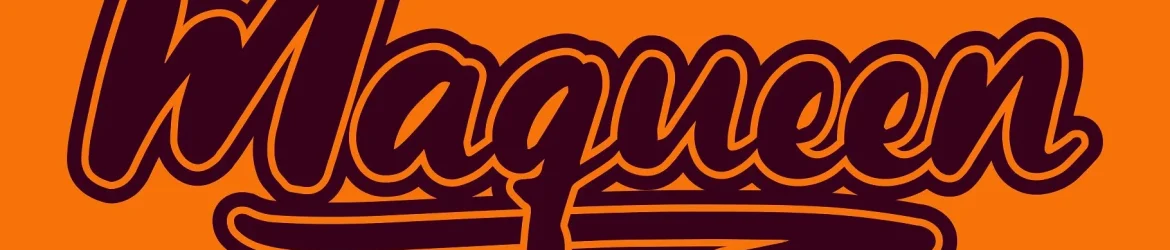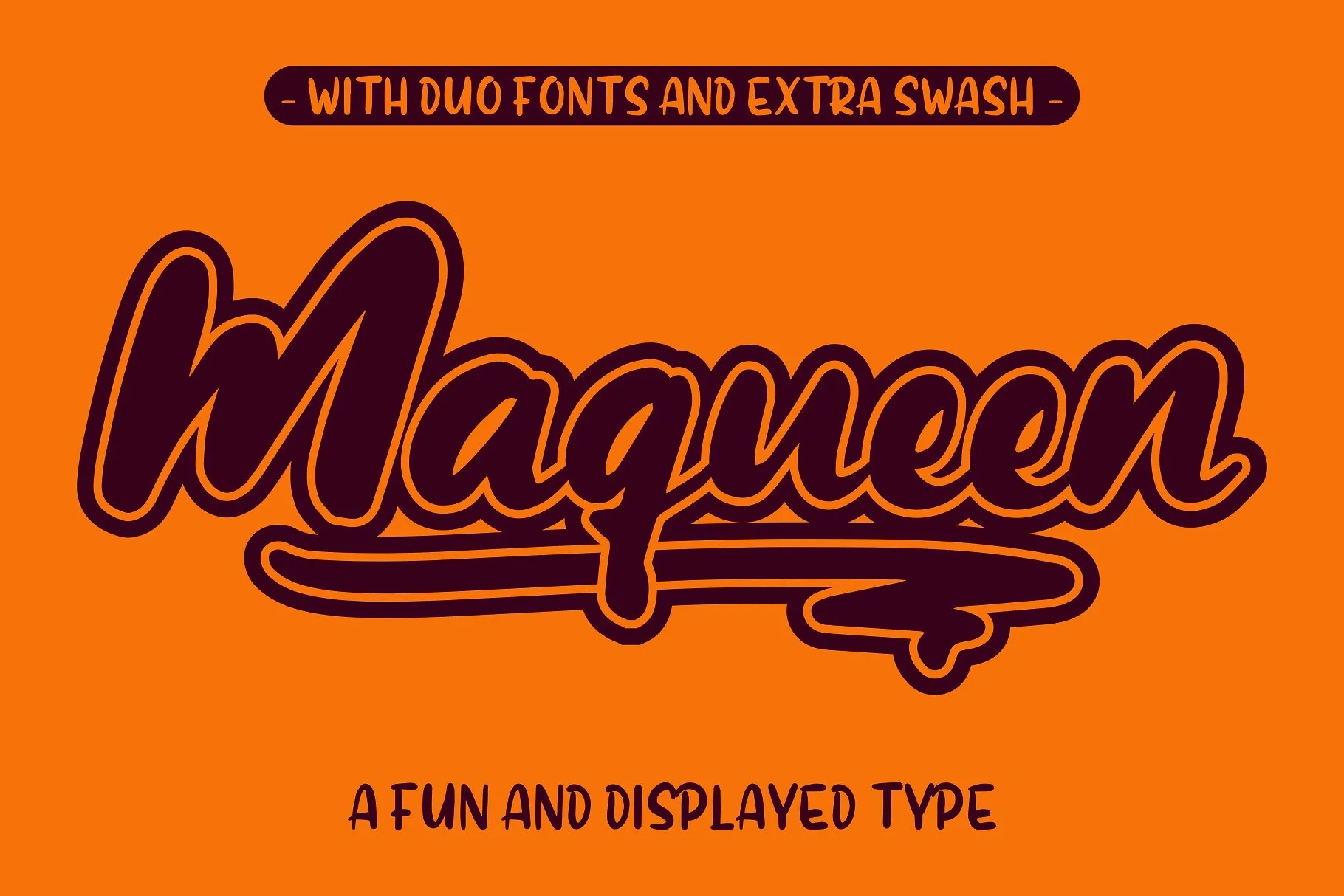
Maqueen Display Font – Fonte Grátis
Maqueen Display Font
Esta é uma fonte script divertida que traz um toque de criatividade para seus projetos digitais. A Maqueen Font permite você criar algo realmente impressionante com seu uso deste tipo bold e vibrante. Introduzimos a Maqueen Font, desenvolvida e compartilhada por Garisman Std. Inspirada em brincadeiras e coisas da infância, o famoso Duo Fonts inclui duas estilos: Display Sans e Semi Script. Esses dois estilos foram projetados para serem usados juntos, permitindo que você use qualquer um dos três estilos como seu estilo principal, mas também pode criar tipografias com múltiplas camadas que compartilham o mesmo olhar visual. Experimente Maqueen Font em seus próximos projetos e inspire-se!